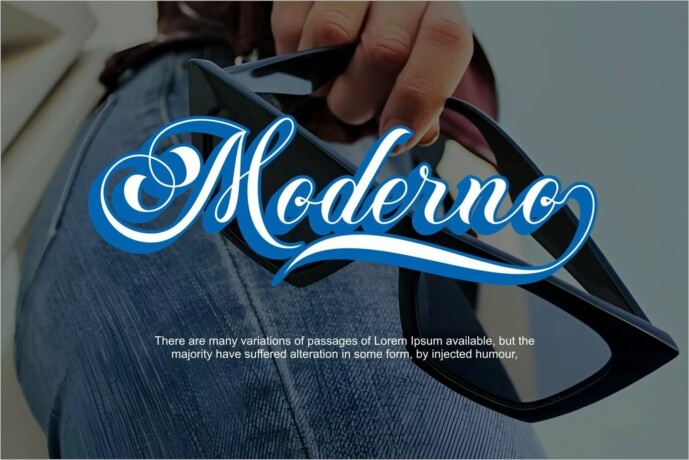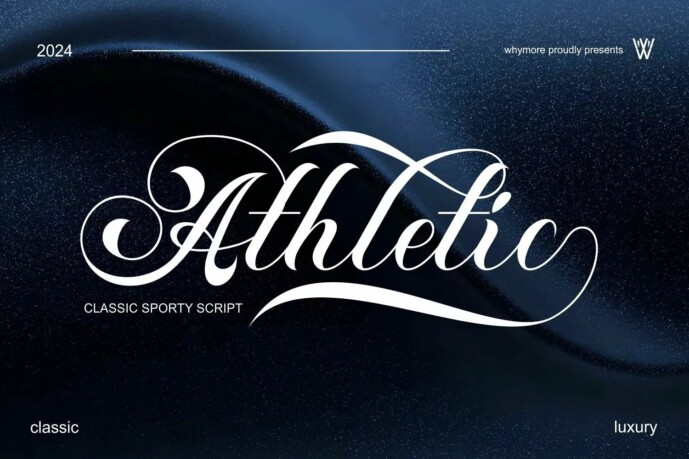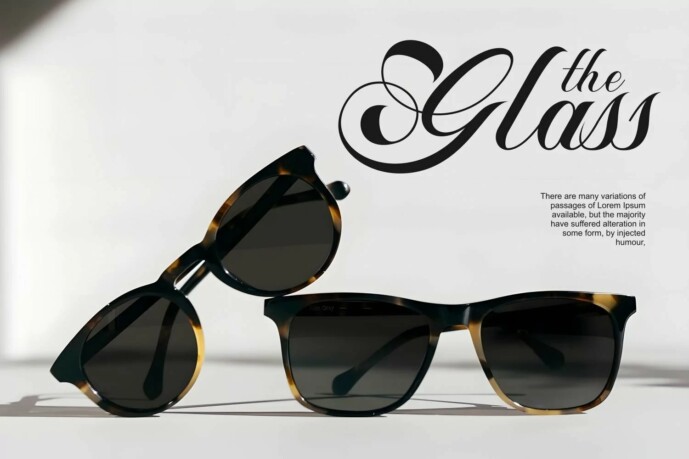
Athletic Font
Athletic Sleek adalah font script modern dengan gaya dinamis, sporty, dan elegan, dirancang khusus untuk proyek desain bertema olahraga, branding, dan merchandise. Dengan tampilan rounded dan halus, font ini memberikan keseimbangan sempurna antara estetika klasik dan kontemporer, menjadikannya pilihan ideal untuk desainer grafis dan kreator konten yang ingin menciptakan karya yang penuh energi dan profesional.